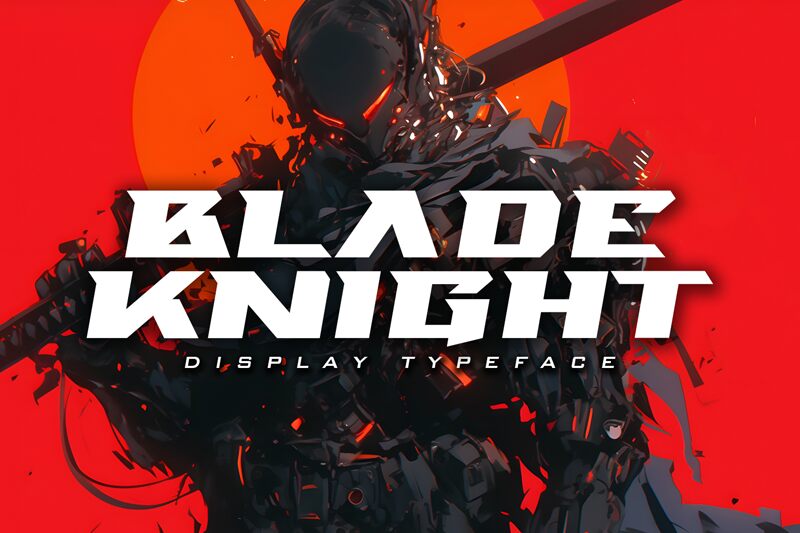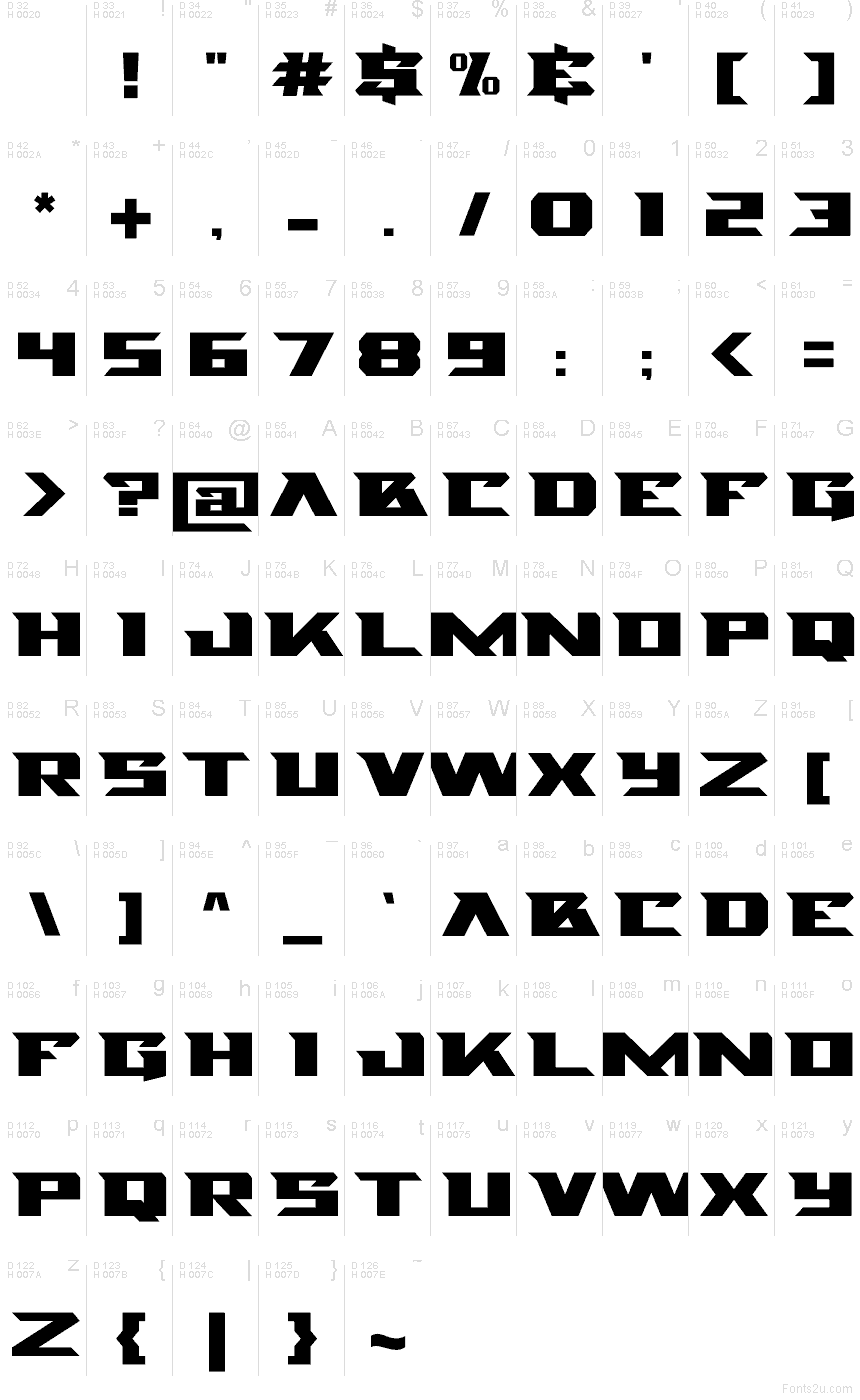
Blade Knight od Maknastudio je bezplatné futuristické písmo typu display, složené z masivních hranatých tvarů písmen. Ostré diagonální řezy a klínovité mezery prorážejí široké tahy a dodávají sazbě opracovaný, pancéřovaný profil. Silueta je úderná a rázná.
Je určeno publiku, které přitahuje sci-fi, akční hry a industriální styl. Obaly her a zábavní plakáty mohou využít jeho hutnou geometrii k navození atmosféry boje, strojů nebo high-tech světů. Na merchandise a v brandingech e-sportů mohou opakované zářezy připomínající čepele připomínat kovové panely, grafiku zbraní a hranaté emblémy.